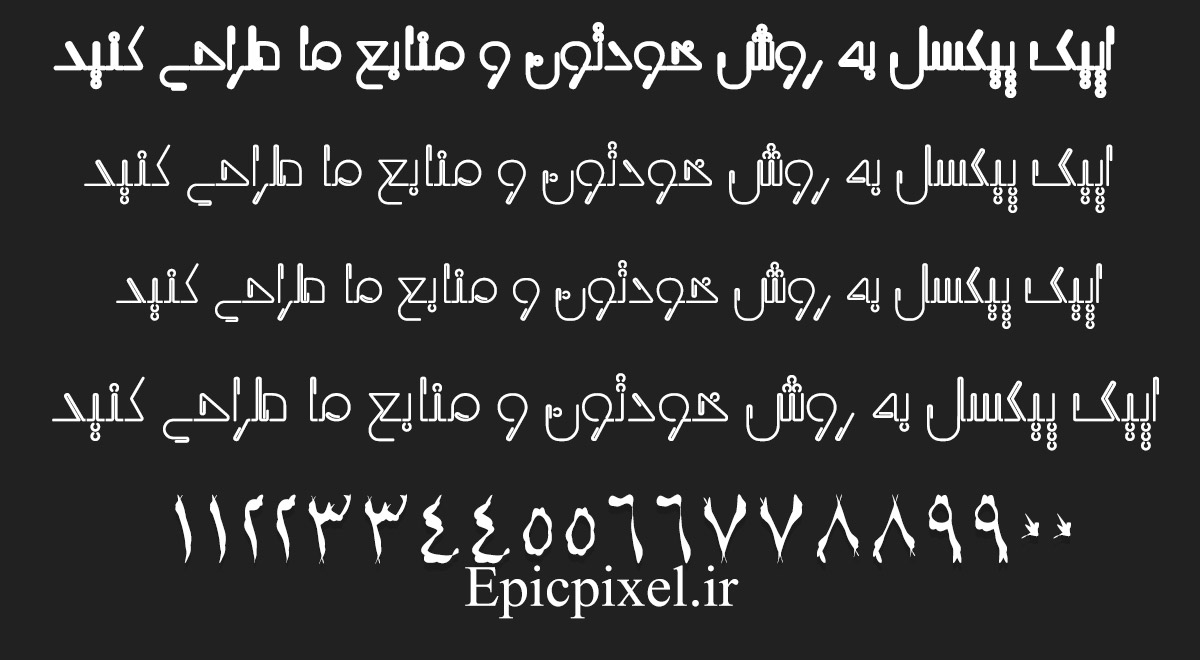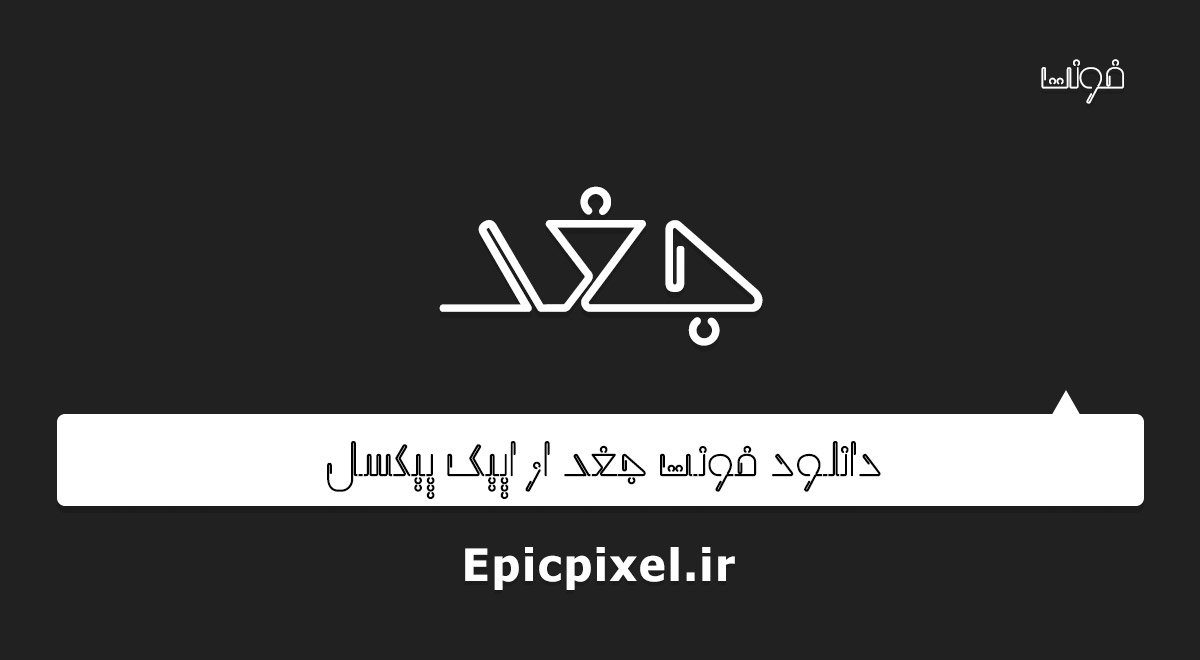
فونت جغد فارسی
دانلود فونت Joghd فارسی Font جغد |
| فونت | دانلود فونت فارسی جغد رگولار Font JOGHD Regular |
اگه من بودم اسمش رو میذاشتم فونت نئون شبیه این نئون های شیشه ای قدیمیه که پشت شیشه مغازه ها کار می کردن…